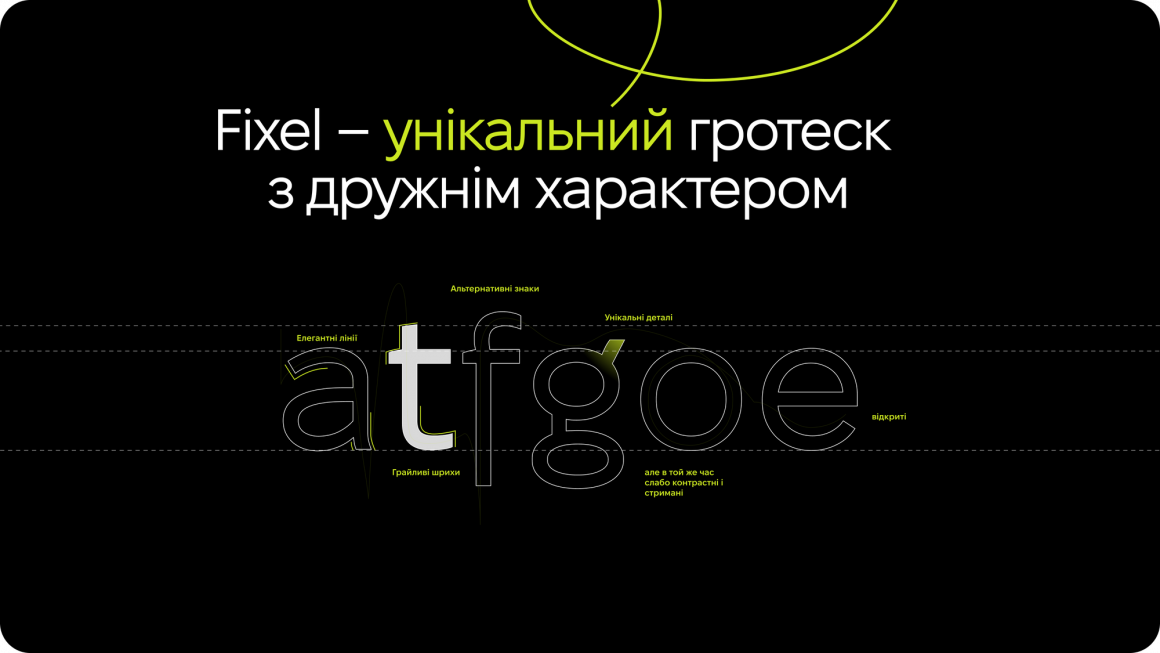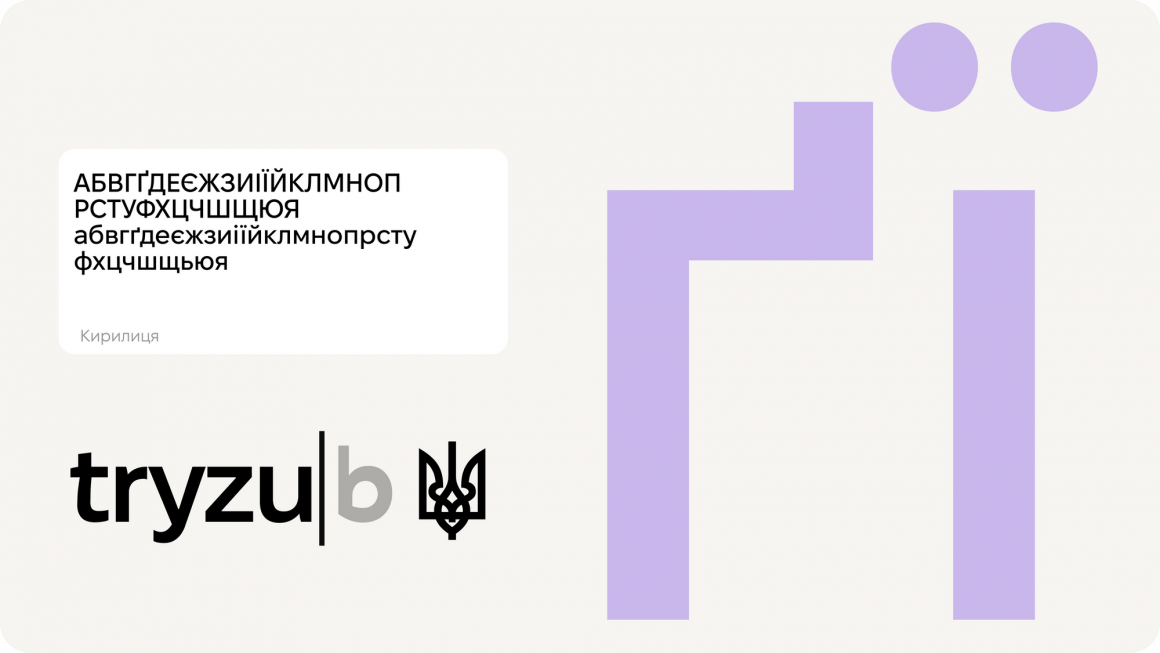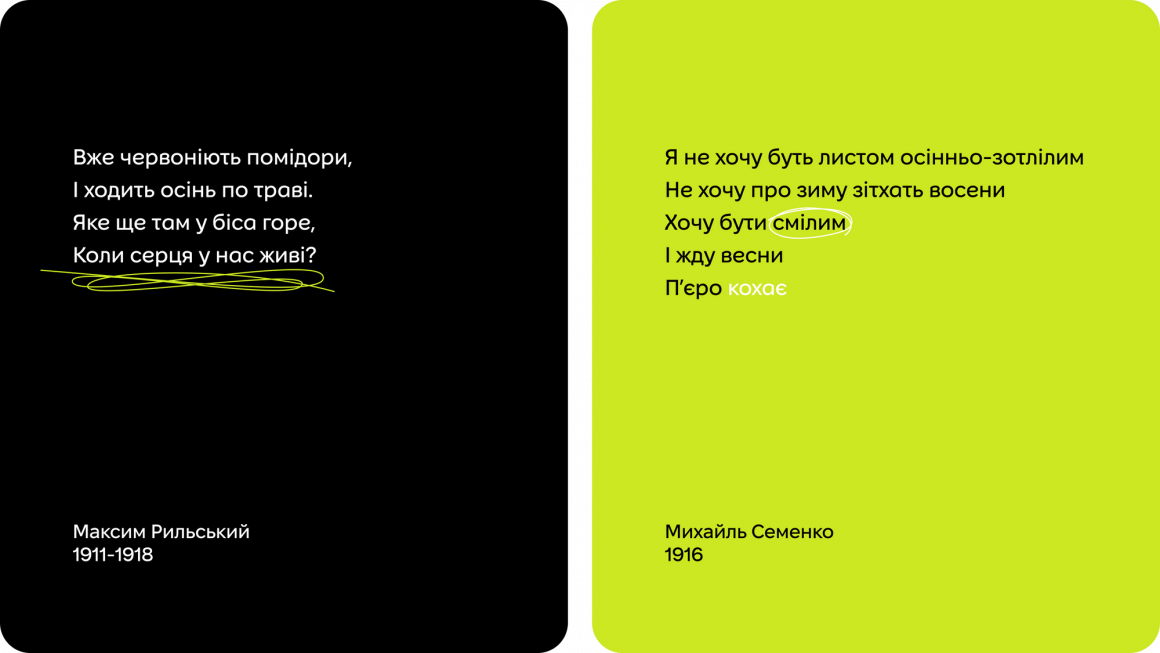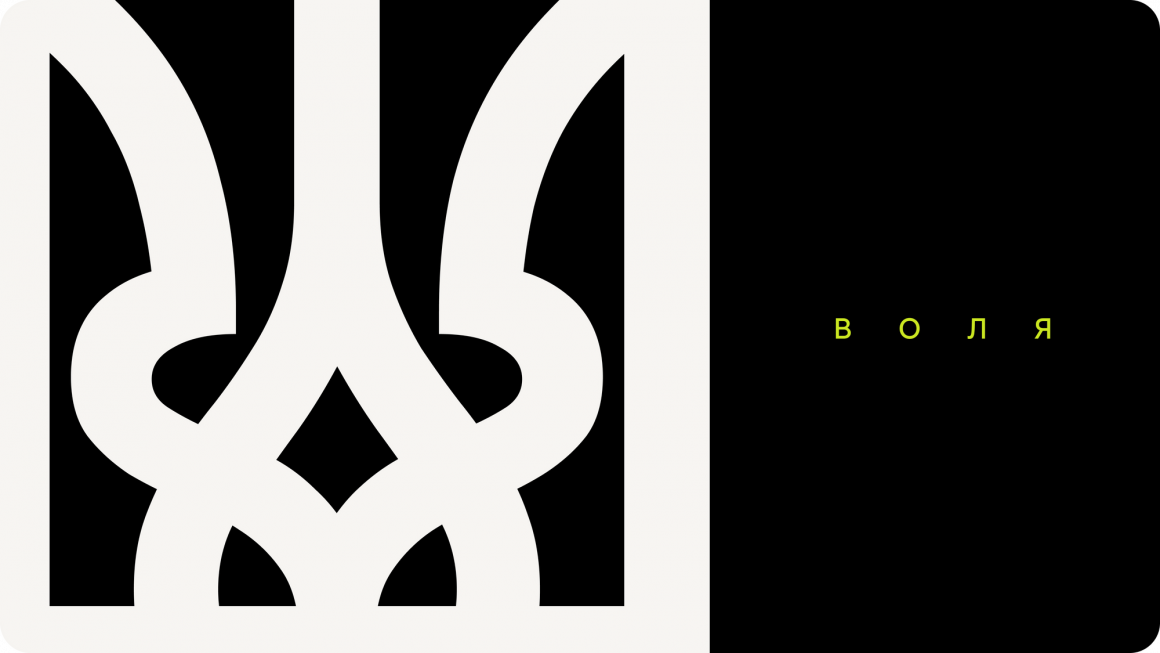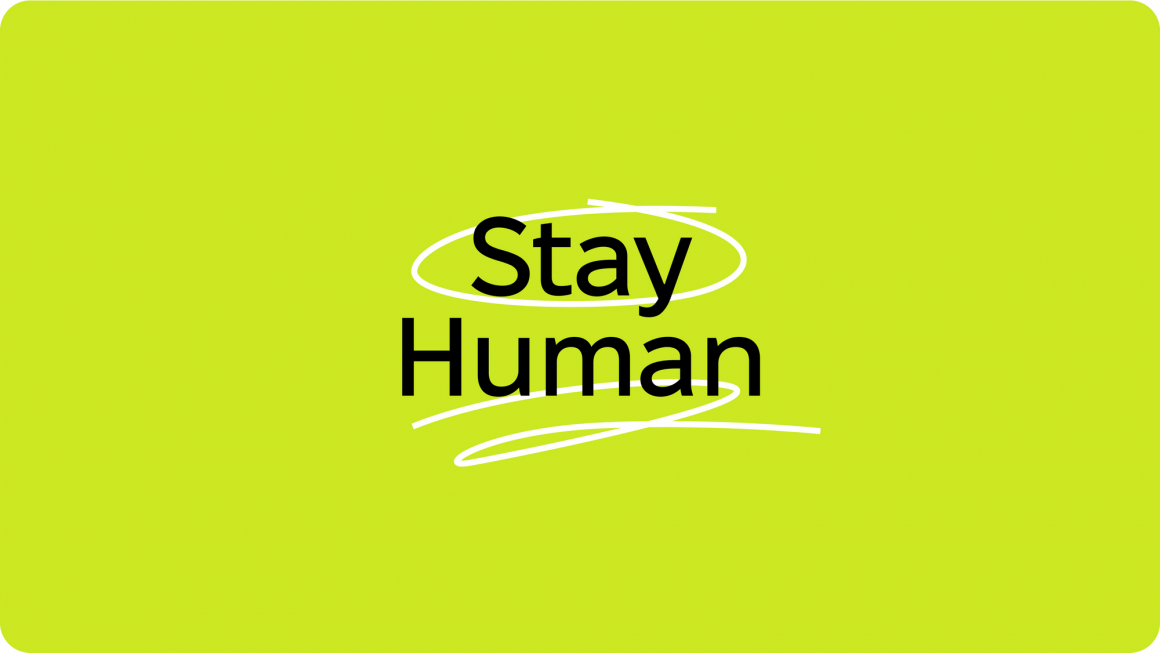
КИЇВ — 9 листопада, 2022 — У День української писемності та мови компанія MacPaw презентувала один із двох власних унікальних шрифтів — Fixel, який створили спільно з українською шрифтовою студією АльфаБраво.
Нові шрифти Fixel та Hoover назвали на честь улюбленців MacPaw — котів, які мешкають у просторі компанії і вже стали невід’ємною частиною її команди та культури. Більш ніж десять років тому Віра Ткаченко, СTIO MacPaw, знайшла Фікселя у підвалі, коли він був ще малим кошеням. Хувер оселився в компанії пізніше, у 2014 році. Їхні характери й зовнішність стали натхненням для розробки особливостей і стилю шрифтів.
Особливості шрифту Fixel
Fixel є варіативним, універсальним і гуманістичним гротеском. У його характері поєднуються чіткість, стриманість і функціональність, а також дружність, динамічність та грайливість. Шрифтова гарнітура представлена у двох варіантах ширини, Text та Display, і дев’яти опціях насиченості — від Thin до Black. Його зручно читати, а завдяки альтернативним накресленням текст можна робити більш впізнаваним та сміливим, що відкриває безліч можливостей для дизайну. Шрифт підійде для роботи із заголовками та великими обсягами тексту.
Окрім набору звичних форм літер та знаків, у шрифті Fixel присутні й альтернативні символи. Вони відрізняються від основних літер, оскільки є більш пластичними, мають посилену динаміку й асиметрію.
Над гарнітурою Fixel працювала команда шрифтових дизайнерів АльфаБраво — Марчела Можина, Сергій Макаренко, Захар Кривошия, Марія Вайнштейн та Кирило Ткачов. Основу стилю заклали Марчела Можина та Сергій Макаренко: Марчела надала шрифту пластичності, гуманності й відкритості, а Сергій підсилив чіткість, геометричність та стриманість. Кирило Ткачов, артдиректор АльфаБраво, наблизив ці підходи, завдяки чому вдалося надати шрифту індивідуальності. Робота над шрифтом тривала близько 10 місяців.
Fixel від MacPaw має у своєму складі розширену латиницю та кирилицю, тому може «розмовляти» більш ніж 40 мовами, зокрема, рідною українською.
Чому вирішили створити власні шрифти?
Раніше у компанії використовували стандартні шрифти. У процесі оновлення айдентики MacPaw вирішили, що власні шрифти зможуть не лише підкреслити індивідуальність бренду, але й допоможуть зробити комунікацію більш впізнаваною і консистентною. Технологічний Fixel та емоційний Hoover відображають цінності компанії й транслюють глобальну ціль MacPaw — to befriend people with technology. Також власні шрифти дозволять бути більш гнучкими: їх можна змінювати разом із розвитком компанії.
«Проєкт MacPaw Fonts почався з бажання покращити консистентність дизайну наших комунікацій. Ми почали шукати партнера, який зміг би разом з нами пройти цей захоплюючий шлях — створення повністю нового унікального шрифту компанії. Для нас було важливо отримати цей досвід разом зі спеціалістами з України. Ми обрали Кирила Ткачова та його студію АльфаБраво.
Ми вирішили безплатно розповсюджувати шрифт Fixel, щоб підтримати спільноту дизайнерів у цей непростий час та отримати цінний фідбек про нашу роботу. Також хочемо розповісти про досвід співтворчості двох команд з України, який був корисним усім учасникам проєкту. Пишаємося тим, що нові шрифти Fixel та Hoover — результат роботи українських дизайнерів, що вкотре показує, які талановиті люди живуть поруч з нами, і коли ми працюємо разом — обов’язково досягаємо своїх цілей», — розповідає Олександр Агєєв, Chief Design Officer MacPaw.
Кирило Ткачов, засновник і артдиректор студії АльфаБраво, про роботу над шрифтом Fixel: «Співпрацювати з MacPaw було цікаво і приємно. Ми багато обговорювали завдання на початку, тестували проміжні результати і шукали ідеї. Це дозволило змінювати роботу і підлаштовувати наш майбутній шрифт для розширених завдань. Шрифтова гарнітура Fixel вийшла об’ємною і складною. Це зробило результат особливим».
Важливою частиною культури MacPaw є її українське походження. Це відображено і в шрифтовій гарнітурі Fixel. Серед альтернативних символів шрифту є український тризуб, дизайн якого розробив український художник та графік Ніл Хасевич у 1949 році. Версія тризуба Хасевича є стильною й лаконічною, і водночас енергійною. Своїми формами, пластикою та характером герб у виконанні Хасевича підходить до сучасного гротеску. У MacPaw та АльфаБраво сподіваються, що Fixel допоможе зберегти та популяризувати спадщину видатного українського художника, а також підкреслить українське походження шрифту.